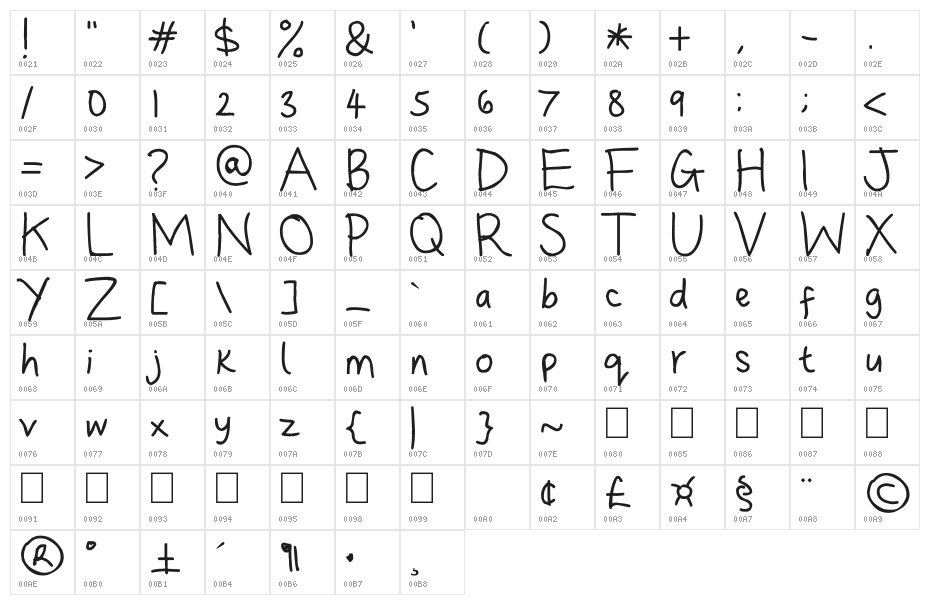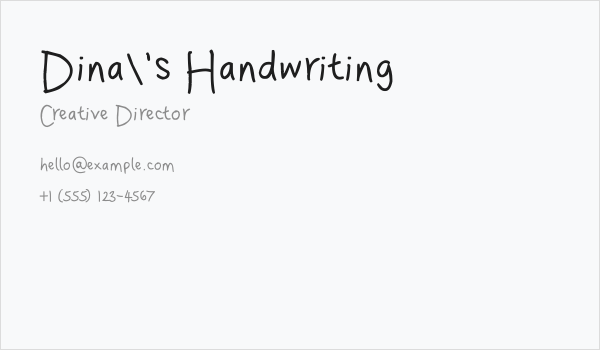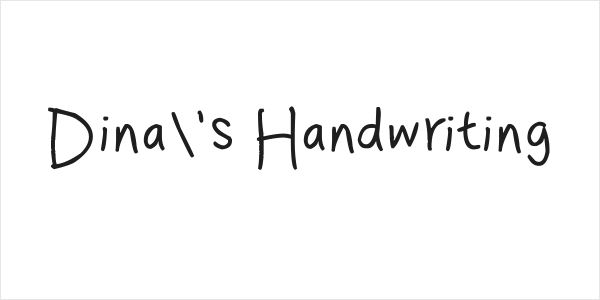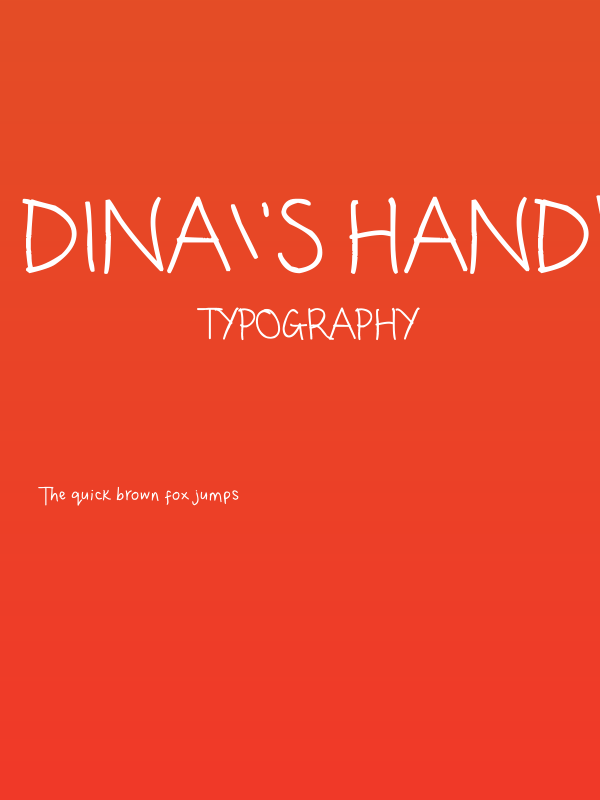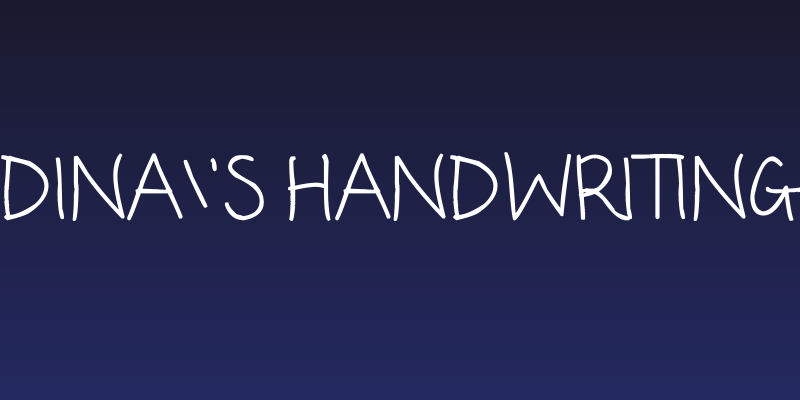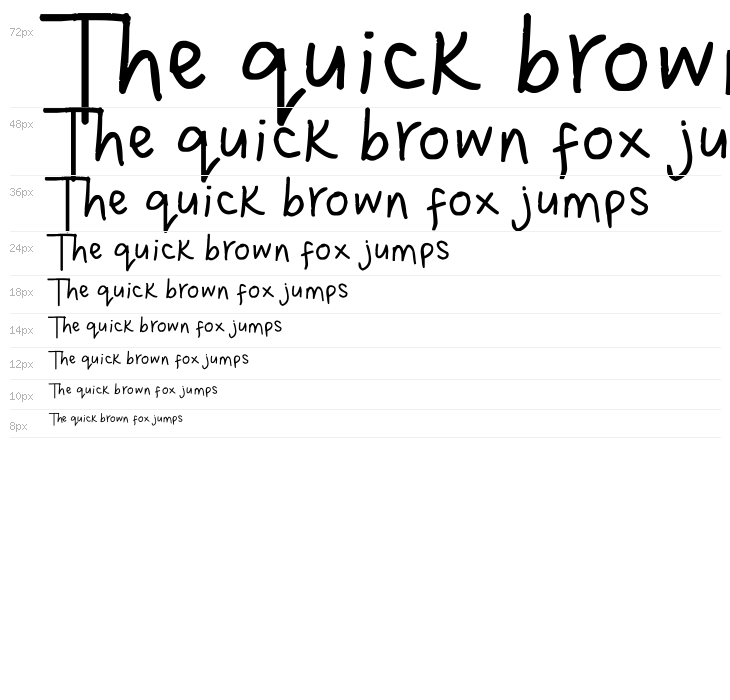
Dina's Handwriting Font
✎ Handwritten
| 整体风格 | Casual, Personal |
| 使用场景 | Headlines, Informal text, Creative projects |
| 推荐项目 | Ideal for greeting cards, personal notes, informal invitations, and creative projects that require a personal touch. |